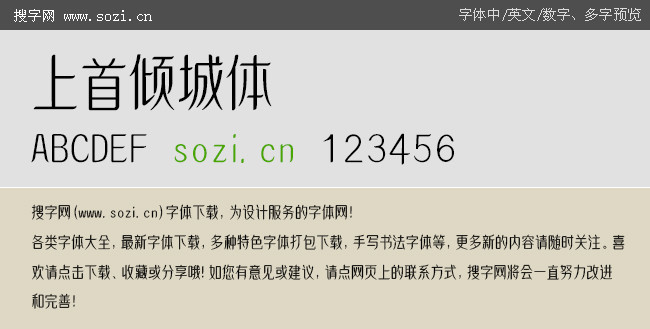
上首傾城體
搜字網(wǎng)給大家提供一款上首傾城體中文字體下載,上首傾城體字體筆畫融入了女性纖細(xì)的線條美感,橫筆進(jìn)行了翹腳顯示了女性的俏皮之感。整體添加了倒圓處理使字體風(fēng)格偏柔和。適用于搭配標(biāo)志、廣告標(biāo)語、商業(yè)廣告等廣告設(shè)計。